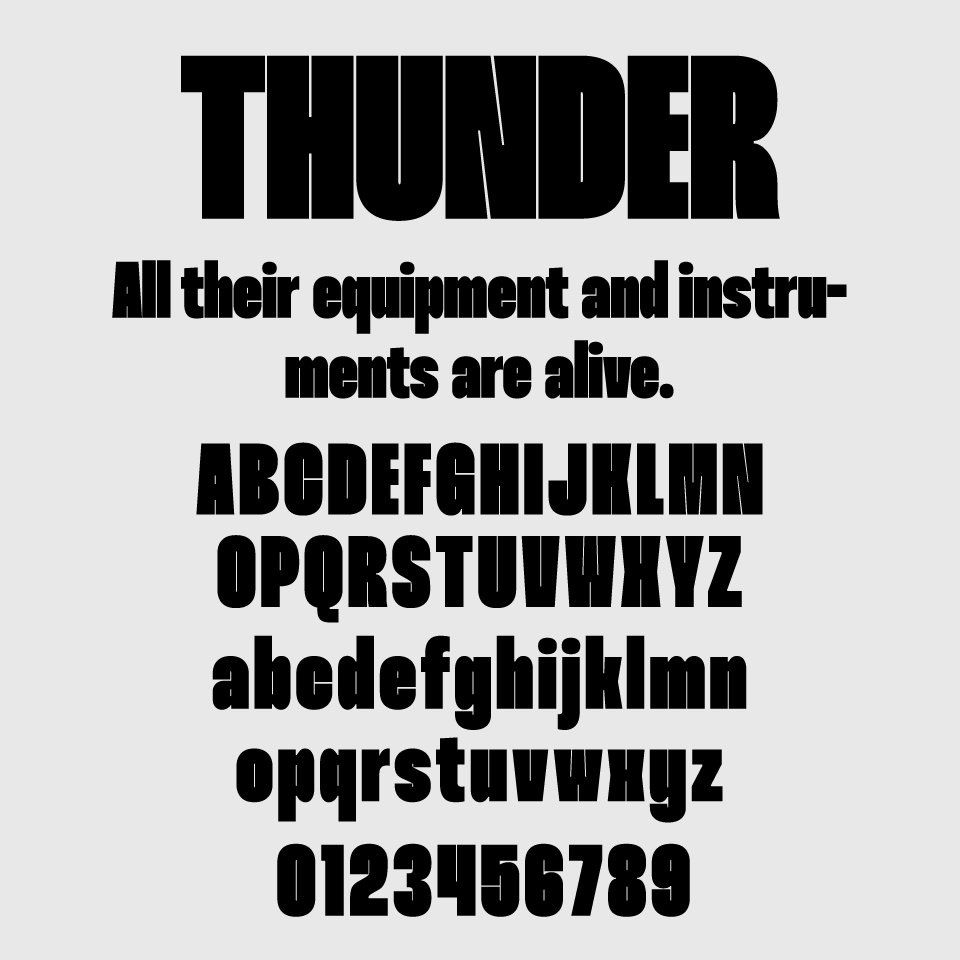
Thunderフォントは、圧倒的な太さと重みが特徴のパワフルなコンデンスド系サンセリフフォントです。
まるでビルのように立ち上がるような超超超極太さで長体なゴシック体で、画面に並べるだけで雷鳴のような存在感を感じるデザインです。
かつ、どこかコミカルで親しみやすい雰囲気もあり、アメコミやポスター、イベントロゴなどで目を引きたいときにぴったりなインパクト重視のフォントです。